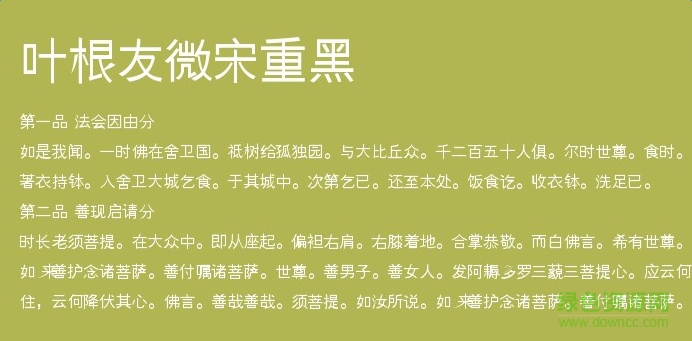
葉根友微宋重黑字體是一款文雅黑風(fēng)格字體軟件,微宋重黑體是葉根友字體系列中比較醒目?jī)?yōu)美的一款字體,字體一筆一畫(huà)工工整整,整體效果十分震撼,還有更多好看字體歡迎來(lái)綠色資源網(wǎng)下載體驗(yàn)!
葉根友微宋重黑字體是一款系列家族字體,有特黑、重黑、中粗、中細(xì)、特細(xì)等,滿足不同排版的需求。
該字體橫豎相間,筆畫(huà)粗細(xì)一致,每個(gè)字體所占空間適中,非常適合用來(lái)文章、論文排版,歡迎下載使用!